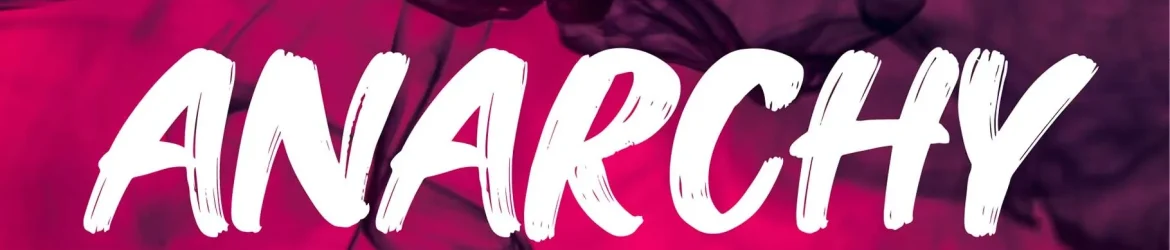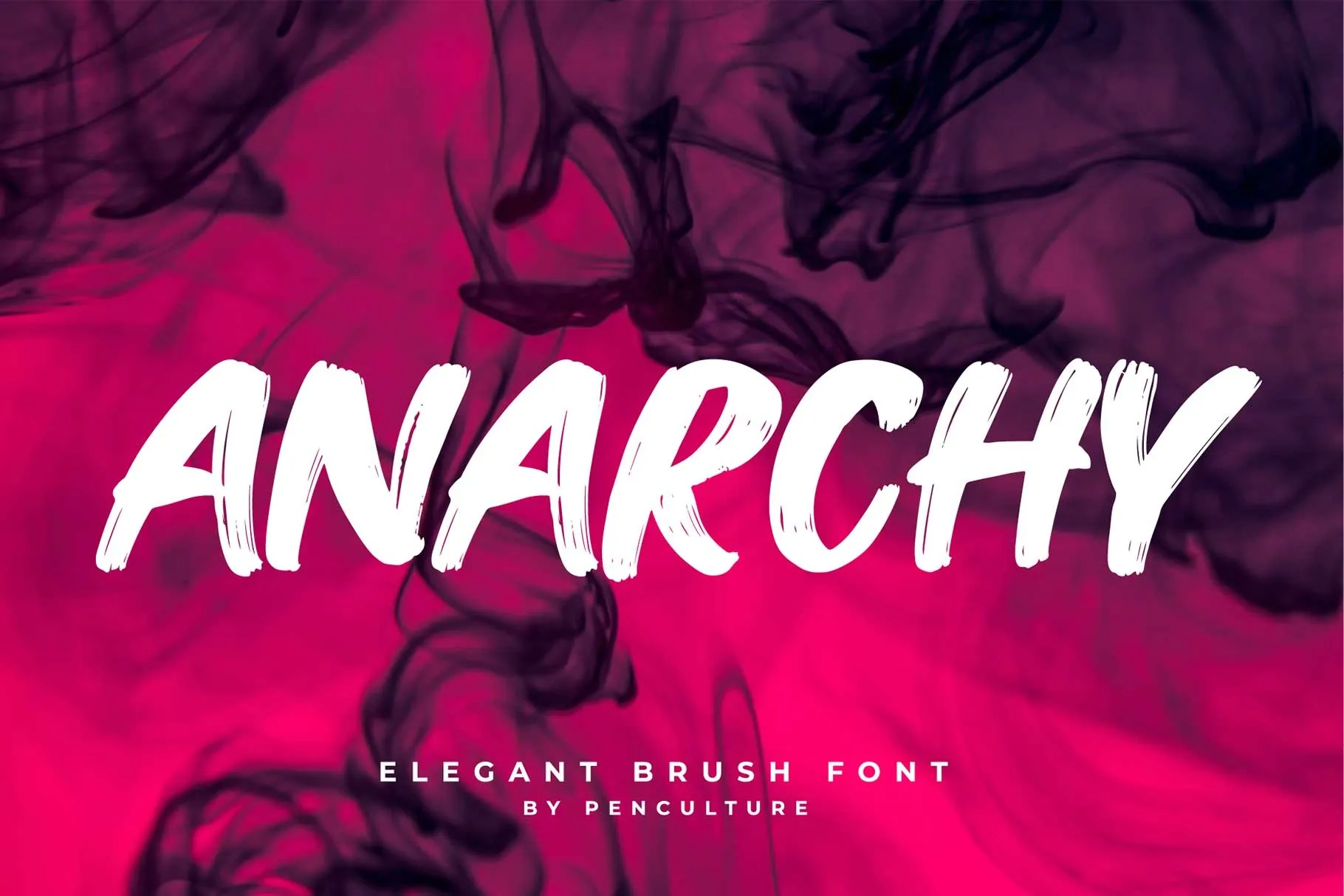
Anarchy Font – Fonte Grátis
Anarchy Font
Anarchy é uma fonte script delicada e elegante, projetada para entregar um apelo único ao seu design. Com traços que flutuam suavemente e carimbos de texto robustos, ela atende perfeitamente a qualquer aplicação de identidade visual, como logos, rótulos ou embalagens. Este tipo de script foi criado pela Pen Culture, mas agora está disponível para compartilhamento por 99designs. Anarchy não apenas transmite elegância e sofisticação com seu formato bold, mas também incorpora caracteres robustos e estendidos que se destacam em diversas aplicações gráficas. A qualidade impressionante desta fonte de esboço o torna uma adição indispensável para sua biblioteca de recursos gráficos. Em um mundo onde a simplicidade pode ser tão poderosa quanto a sofisticação, Anarchy oferece precisamente isso: beleza e funcionalidade em um só design inovador.